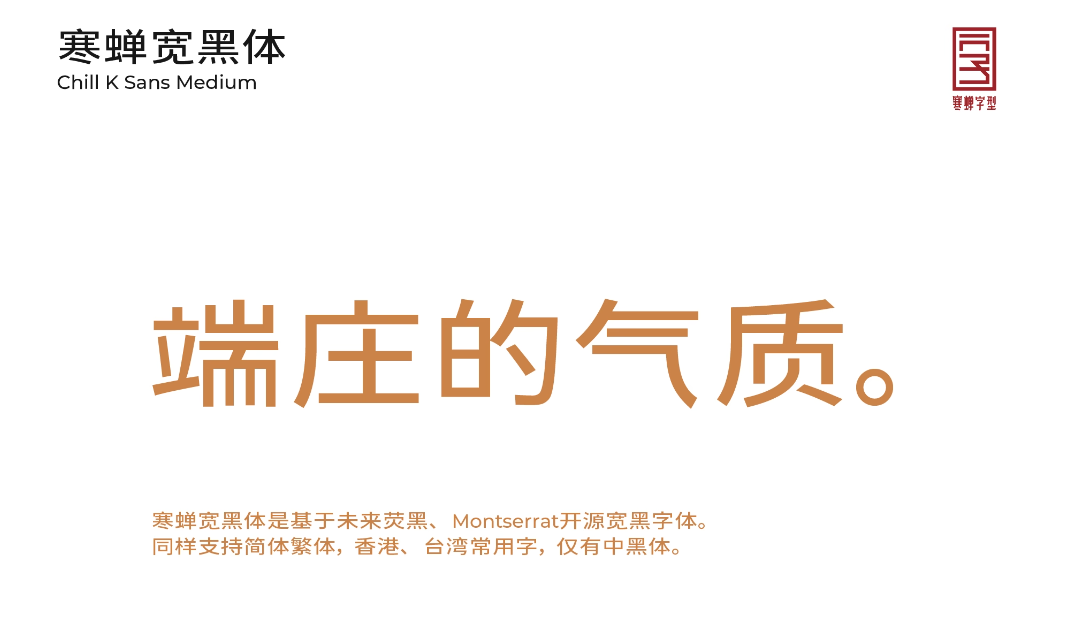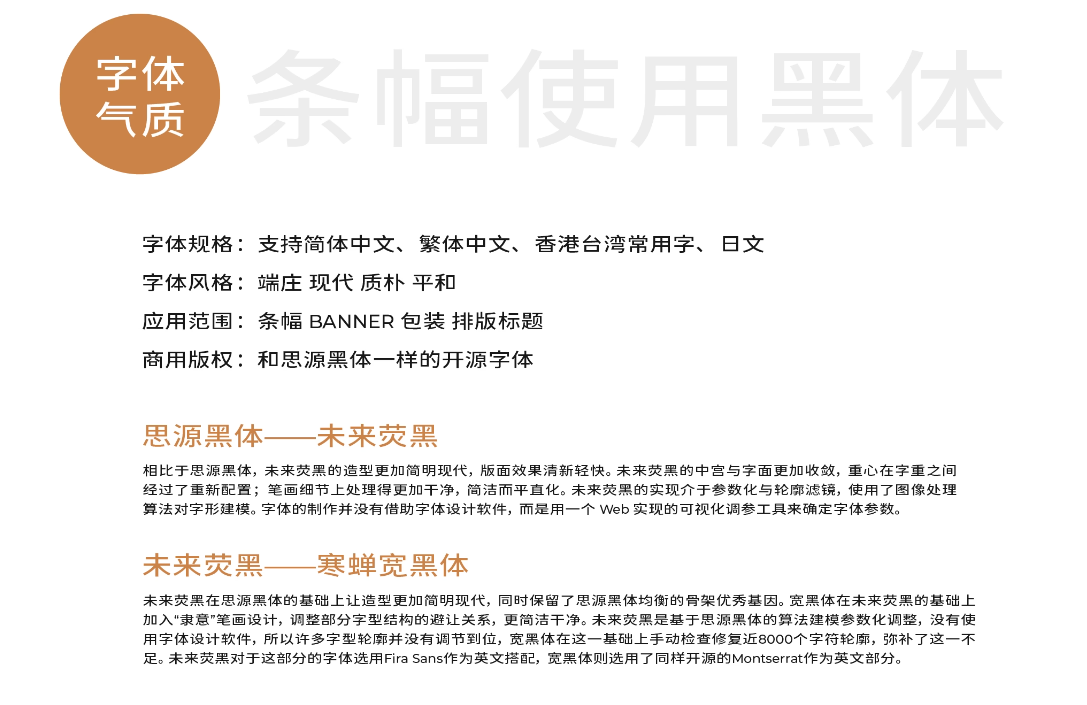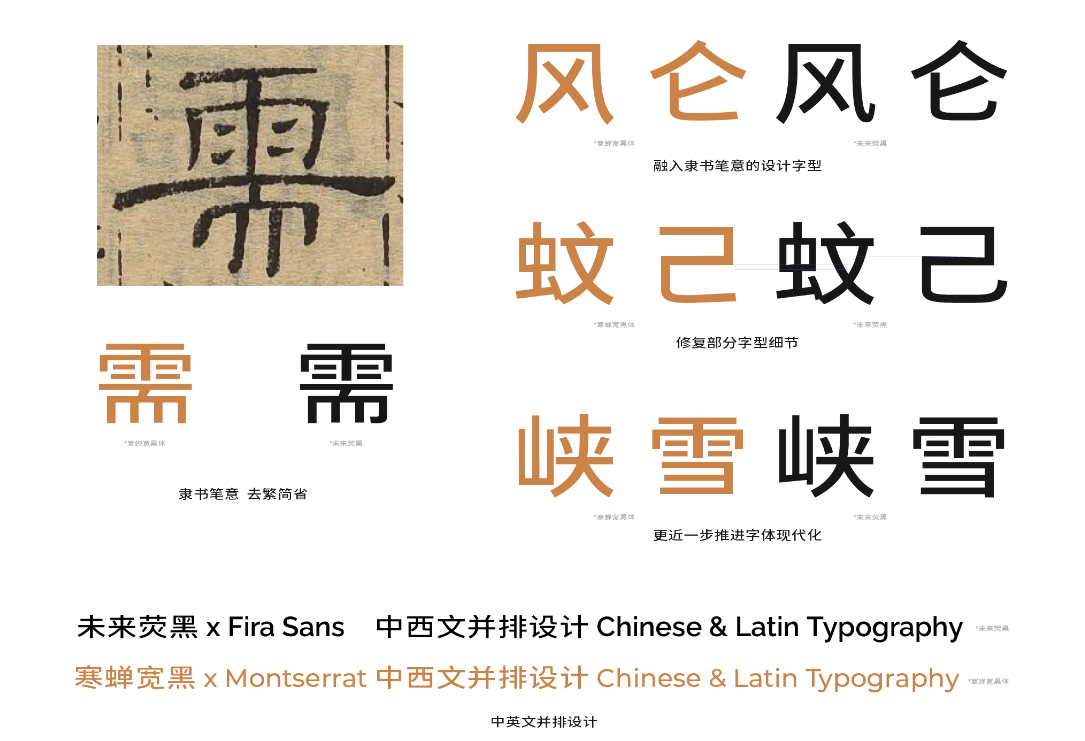
寒蝉宽黑体(Chill K Sans)是基于思源黑体,以未来荧黑为框架,融入传统隶书笔意设计的一款免费开源中文字体。
由于未来荧黑是通过算法生成的字体,所以轮廓细节有很多不足之处。为此,寒蝉宽黑体团队手动修复了近8000个字符轮廓,使其更精准更简洁更清晰。支持简体中文、繁体中文、香港台湾常用字及日文,英文部分则选用了同样开源的 Montserrat 字体,可以与中文风格完美契合。